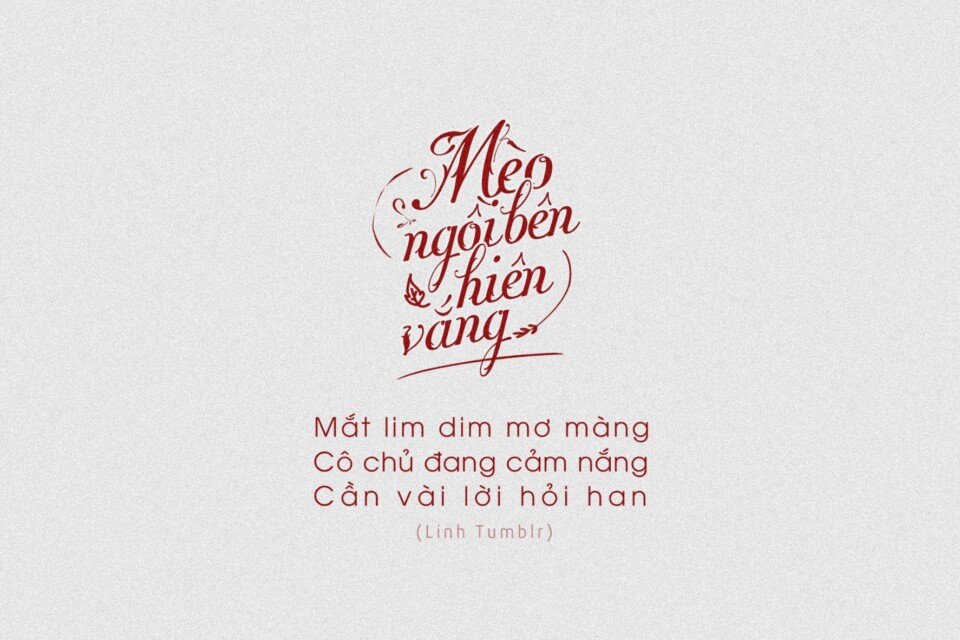
Tải Font Việt hóa MTD Fleurie Miễn Phí: Lựa Chọn Tuyệt Vời Cho Thiết Kế Sáng Tạo
Trong thế giới thiết kế đồ họa và typography, việc tìm kiếm một Font Chữ đẹp, độc đáo, và quan trọng nhất là đã được Việt hóa hoàn chỉnh luôn là ưu tiên hàng đầu. Đặc biệt đối với học sinh, sinh viên hay những người chuẩn bị cho các dự án tốt nghiệp, một phông chữ ấn tượng có thể nâng tầm chất lượng bài trình bày. Hôm nay, chúng ta sẽ cùng khám phá và tìm hiểu về Font Việt hóa MTD Fleurie – một tuyệt phẩm chữ viết tay (handwriting) mang phong cách thư pháp hiện đại, đang làm mưa làm gió trong cộng đồng designer Việt Nam. Sự kết hợp giữa nét mềm mại, uyển chuyển cùng tính năng hỗ trợ đầy đủ dấu tiếng Việt khiến MTD Fleurie trở thành công cụ không thể thiếu cho các ấn phẩm từ thiệp mời, logo, đến thiết kế bìa sách và đồ án tốt nghiệp. Hãy cùng đi sâu vào những đặc điểm nổi bật và cách sử dụng hiệu quả loại font chữ tuyệt vời này.
Đặc điểm và nhu cầu sử dụng Font Việt hóa MTD Fleurie trong giáo dục và thiết kế
MTD Fleurie ban đầu là một phông chữ script quốc tế, nổi tiếng với sự tinh tế và cấu trúc chữ cái bay bổng. Tuy nhiên, nếu không được Việt hóa, font này sẽ gặp vấn đề nghiêm trọng khi sử dụng các dấu tiếng Việt, dẫn đến lỗi font hoặc mất thẩm mỹ. Đây là lý do tại sao phiên bản Font Việt hóa MTD Fleurie lại quan trọng đến vậy, đặc biệt là với học sinh, sinh viên cần tạo ra những sản phẩm chuyên nghiệp, không mắc lỗi chính tả. Phiên bản Việt hóa đảm bảo rằng mọi ký tự, bao gồm cả các dấu thanh, đều được hiển thị một cách hài hòa và đồng nhất với phong cách thiết kế gốc. Nó giúp các bạn trẻ dễ dàng tạo ra những tiêu đề bài báo cáo, poster sự kiện trường học, hay thiệp chúc mừng tốt nghiệp thật sự thu hút, góp phần tăng điểm ấn tượng cho các bài thi cuối cấp hoặc bảo vệ luận án.
Ứng dụng đa dạng của MTD Fleurie cho các dự án học tập và nghề nghiệp
Không chỉ dừng lại ở tính thẩm mỹ cao, MTD Fleurie còn mang tính ứng dụng rất lớn. Đối với các đồ án cuối khóa hoặc luận văn cần yếu tố sáng tạo, font chữ này giúp phần tiêu đề trở nên nổi bật hơn so với các font sans-serif truyền thống. Sinh viên thiết kế đồ họa thường xuyên sử dụng nó cho các mock-up bao bì, nhận diện thương hiệu cá nhân, hay các dự án minh họa cần sự lãng mạn, cổ điển nhưng vẫn giữ được nét hiện đại. Các bạn học sinh cấp 3 có thể dùng MTD Fleurie để thiết kế các bìa sổ tay, các trang trình chiếu (slide) báo cáo khoa học, hay thậm chí là poster tuyên truyền cho các hoạt động ngoại khóa. Tính linh hoạt và độc đáo của nó là điểm mạnh giúp sản phẩm của người dùng khác biệt hóa. Hơn nữa, những nét chữ mềm mại, uyển chuyển của MTD Fleurie rất phù hợp cho các thiết kế liên quan đến ngành thời trang, mỹ phẩm, hoặc các sản phẩm thủ công.
Tối ưu hóa thiết kế với các tính năng nâng cao của MTD Fleurie Việt hóa
Một trong những yếu tố làm nên sức hấp dẫn của MTD Fleurie chính là bộ ký tự thay thế (alternates) và các nét nối (ligatures) phong phú, thường thấy ở các font chữ thư pháp cao cấp. Khi được Việt hóa cẩn thận, những tính năng này vẫn hoạt động trơn tru trong các phần mềm thiết kế chuyên nghiệp như Adobe Photoshop, Illustrator hay cả trong Microsoft Word (với một số điều chỉnh). Điều này cho phép người dùng tùy biến độ “bay bổng” và “nghệ thuật” của văn bản theo ý muốn, tạo ra các biến thể độc đáo mà font chữ thông thường không thể làm được. Để đạt được hiệu quả SEO tốt nhất, các nhà thiết kế cần lưu ý rằng việc sử dụng font chữ phù hợp giúp thông điệp truyền tải rõ ràng và ấn tượng hơn, qua đó gián tiếp cải thiện trải nghiệm người dùng trên website hoặc sản phẩm số. Việc khai thác tối đa các ký tự đặc biệt sẽ giúp văn bản của bạn không chỉ là chữ viết mà còn là một tác phẩm nghệ thuật.
Ngoài ra, khi sử dụng MTD Fleurie, bạn nên kết hợp nó với các font chữ đơn giản hơn (như sans-serif) cho phần nội dung chính để đảm bảo tính dễ đọc. MTD Fleurie nên được dành riêng cho các tiêu đề, điểm nhấn, hoặc chữ ký, nơi mà sự sáng tạo và phong cách được đặt lên hàng đầu. Điều này giúp tối ưu hóa khả năng đọc hiểu của người xem, một yếu tố cực kỳ quan trọng trong các bài thuyết trình học thuật hay các tài liệu ôn thi.
Tóm lại, sự xuất hiện của Font Việt hóa MTD Fleurie đã mang lại một làn gió mới cho cộng đồng thiết kế Việt Nam, đặc biệt là trong môi trường học thuật. Với vẻ đẹp thư pháp thanh lịch và khả năng hỗ trợ tiếng Việt hoàn hảo, nó xứng đáng là lựa chọn hàng đầu cho các bạn học sinh, sinh viên mong muốn tạo ra những sản phẩm sáng tạo và chuyên nghiệp. Đừng ngần ngại khám phá và áp dụng font chữ này vào dự án tiếp theo của mình. Việc lựa chọn Font Chữ phù hợp không chỉ là vấn đề thẩm mỹ mà còn là yếu tố quyết định đến sự thành công và ấn tượng của tác phẩm. Hãy tải ngay MTD Fleurie Việt hóa để bắt đầu hành trình sáng tạo của bạn.